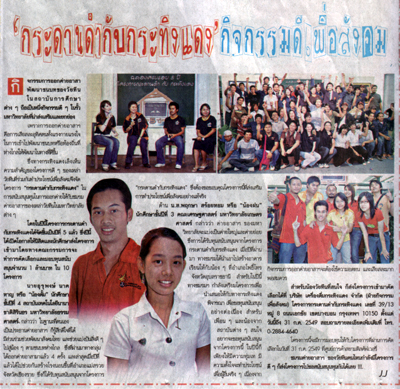
ลักเด็กในเดลินิวส์
ลักเด็ก กิจกรรมดีเพื่อสังคม  :42:
ฉบับเมื่อวานหรือวันก่อนก็มีลักเด็กเหมือนกัน
สงสัยคนทำคงติดใจ เลยลักใหญ่เลย  :42:
เมื่อวานไปร้านหนังสือ เจอลักเด็กแบบแปลกๆ  :42:
เค้าลบขอบเส้นกระดาษออก ไม่เป็นไรๆ จำได้ๆ
งั้นก็ได้อีกหนึ่งไอเดียเลยสิครับ
ทำลักเด็ก เวอร์ชั่นไม่มีกรอบกระดาษเป็นตัวต่อไป  :12:
กับอีกตัว มีแต่กรอบไม่มีอักษร  :43:
เคยคิดจะทำเหมือนกันครับ แต่มันจะลักเด็กถี่ไปนิด
กะว่าจะทำฟอนต์แบบอื่นก่อน แล้วค่อยกลับมาลักเด็กอีกที